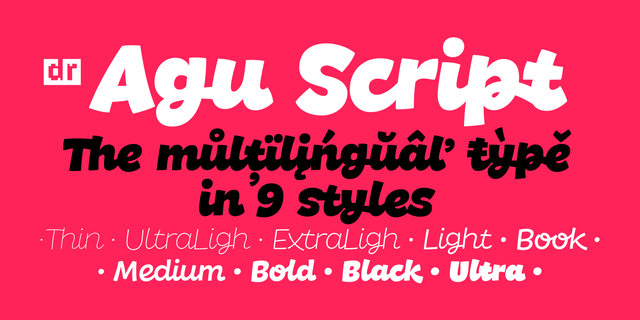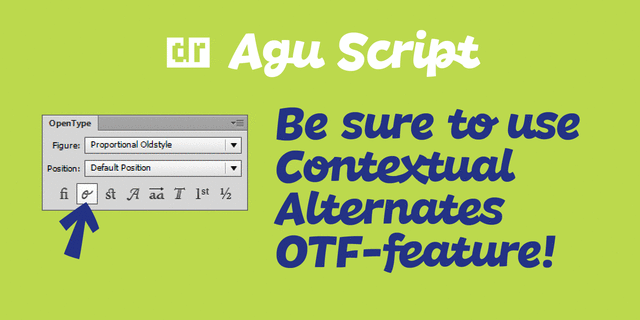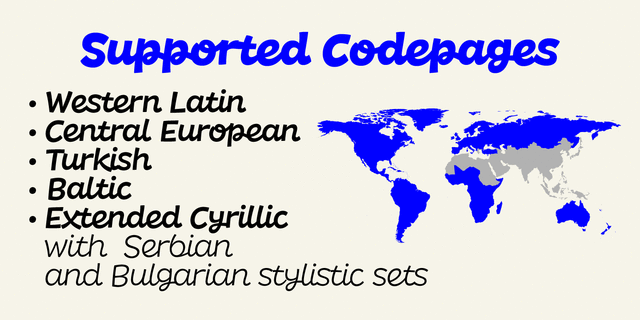
Шрифт Агу Скрипт – это семейство с набором из девяти курсивных начертаний от сверхсветлого до сверхжирного. Может применяться для неформальных текстов, детских книжек и приложений. Шрифт разработан Дмитрием Растворцевым в 2016 году.
7-е из 9 начертаний
веселый, задорный, смешной, дружелюбный, добродушный, добрый, радостный, прыгающий, неряшливый, игривый, приветливый, озорной, непоседливый, подвижный, оригинальный, свежий, спелый, вкусный, тяжелый, заметный, броский, детский, наивный, карикатурный, милый, мультяшный, новогодний, остроумный, домашний, летний, счастливый, прикольный, динамичный
детская книжка, канцтовары, карандаши, школа, лагерь, юмор, тетрадь, анимация, завтрак, игрушка, детское питание, еда, закуска, зоопарк, клоун, раскраска, игра, пицца, зоомагазин, животные, отдых, дневник, цирк, мультфильм, новый год, базар, детский сад, утренник, Christmas, селфи, каникулы, десерт, мороженное, смузи, наклейка, стикер, инстаграм Стилистика: